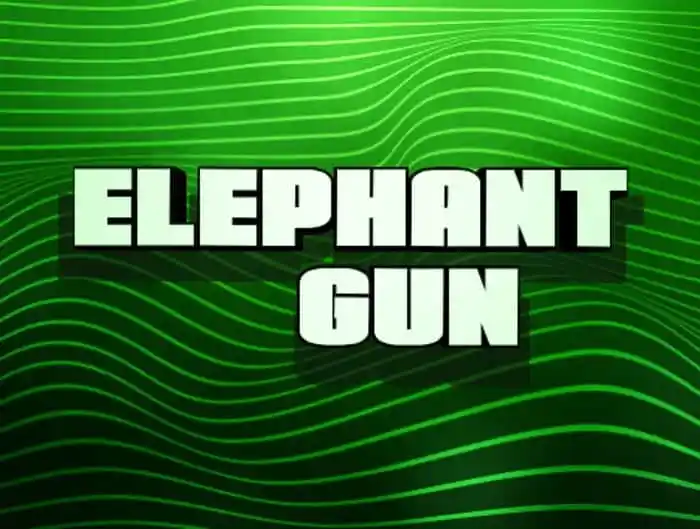
A Elephant Gun Display Font é uma escolha única para aqueles que buscam uma fonte com personalidade em suas criações visuais. Com 22 versões diferentes, incluindo Regular, Italic, Condensed e Expanded, esta família de letras oferece um leque de opções perfeito para estilos de design mais chamativos. Os designers têm a oportunidade de explorar diferentes graus de impacto visual com as versões Super-Italic, Halftone e Gradient. Além disso, a presença da versão 3D permite criar ambientes tridimensionais inovadores em qualquer projeto. A Elephant Gun Display Font é uma excelente adição para designers que buscam personalizar o texto de maneira atraente e moderna, criando letras que chamam a atenção imediatamente. Seja no design editorial, publicitário ou até mesmo nos jogos digitais, essa fonte certamente impressionará seus usuários com sua identidade única e poderoso impacto visual.